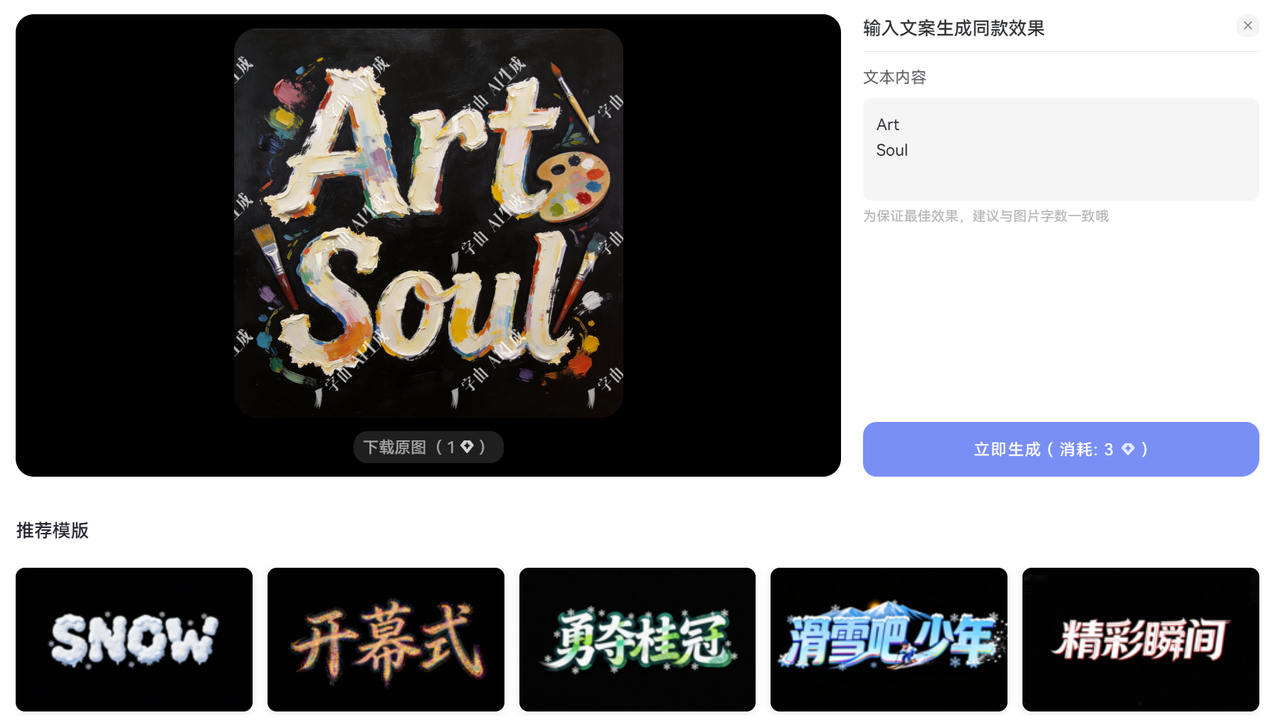
轻松自制二次元字体,分享4款好用的二次元字体生成工具
字体在二次元这个颜值至上的创作世界里,是极具辨识度的视觉核心。一款贴合风格的二次元字体,不仅能传递文字信息,更能渲染画面氛围、契合创作调性。很多朋友可能觉得 “二次元字体制作” 听起来门槛超高,但别担心,我今天就是来给大家 “降维打击” 的,推荐一些无论是萌新爱好者还是资深设计达人,都能轻松上手的二次元字体制作工具。
字由网:零基础也能秒出二次元字体的 AI 神器
说到二次元字体制作,字由网(https://www.hellofont.cn/font-tools)的 AI 字体功能必须放在首位,哪怕是刚接触字体设计的新手,也能在几分钟内做出有质感的作品。
打开字由网顶部的菜单栏的 AI 字体工具页面,首先会被它丰富的模板库惊艳到。这里的模板不是简单的字体样式堆砌,而是精准匹配二次元常见风格 。
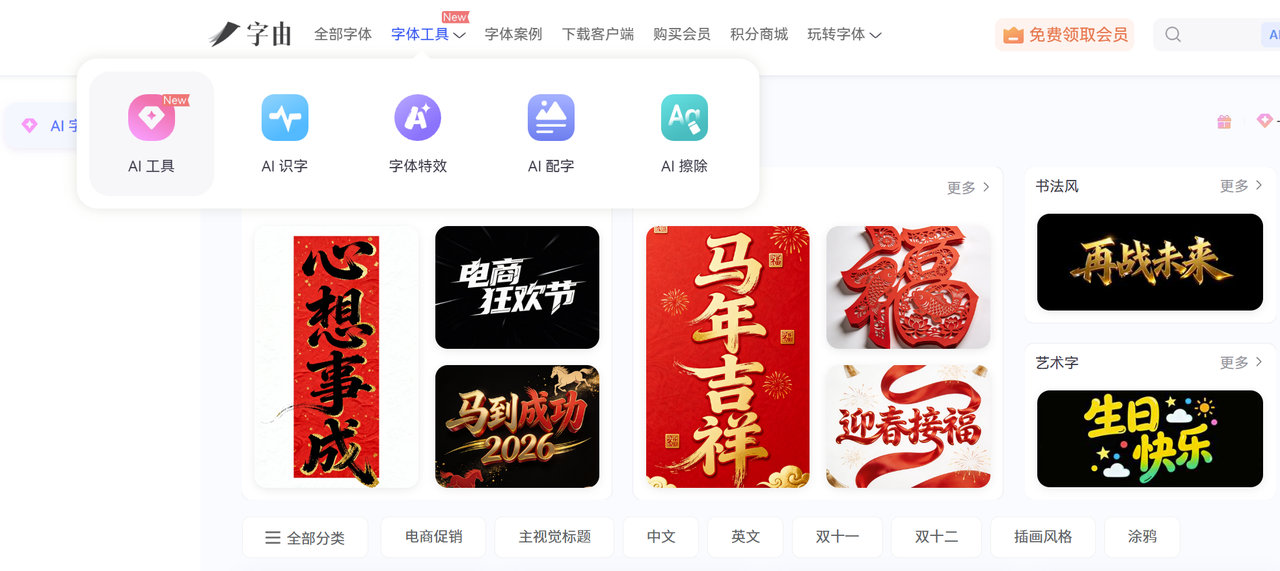
操作过程更是简单到 “傻瓜式”:先在模板库中选中心仪的风格,点击进入编辑页面后,直接输入想要生成的文字,比如 “再战未来”“生日快乐”,系统会在 3 秒内生成对应的特效字体图片。
生成的字体不仅风格统一,还支持透明背景下载,下载后能直接导入 PS、剪映等工具进行二次创作,无论是做漫画封面标题,还是视频动态字幕,都能无缝衔接。
字由网的 AI 字体模板会定期更新,紧跟二次元潮流趋势,比如近期热门的 “赛博朋克光效字”“复古像素字” 都能及时找到。对于想快速出效果、又没有设计基础的用户来说,字由网绝对是性价比最高的选择。
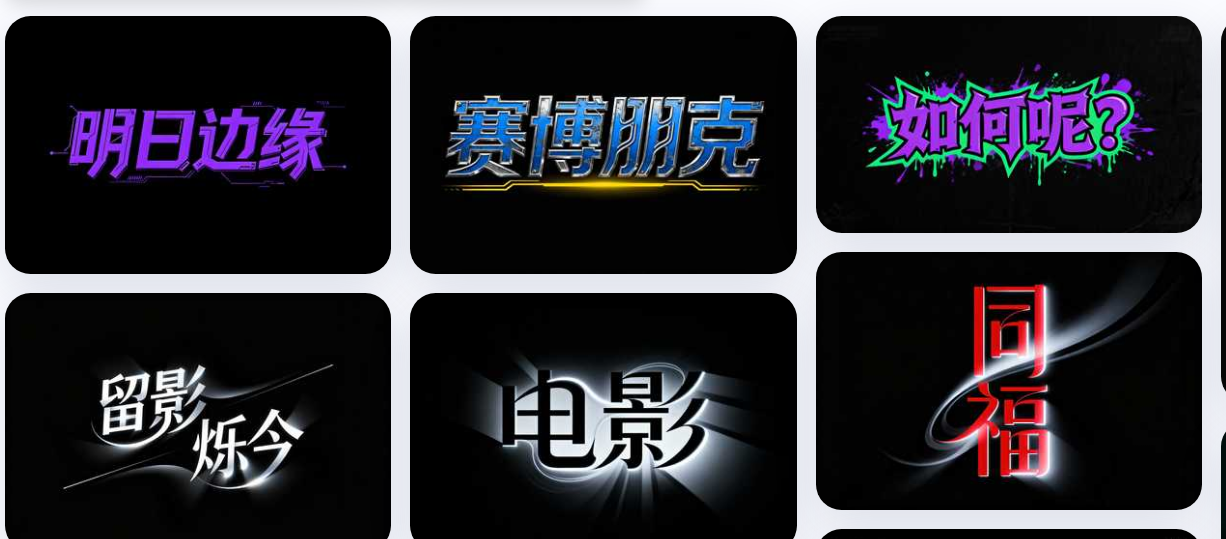
Clip Studio Paint:动漫迷专属的手绘字体优化工具
如果你想让二次元字体更有 “手绘温度”,不满足于 AI 生成的标准化效果,那 Clip Studio Paint(简称 CSP)绝对是不二之选。这款软件是动漫圈的 “宝藏工具”,不仅能画漫画,在字体设计上也有独特优势。最适合二次元创作的是它的 “特效字辅助工具”,比如制作漫画中的拟声词 “轰!”“咻~~”,可以用 “自由变换” 工具把字体拉长成速度感十足的形状,再用 “喷溅笔刷” 在笔画边缘添加墨水飞溅效果,瞬间让文字 “活” 起来。
FontSpace:免费二次元字体库 “富矿”
如果只是偶尔需要使用二次元字体,不想花时间自己设计,那 FontSpace 这个免费字体网站就能帮上大忙。它收录了上万款风格各异的字体,其中二次元主题字体数量超多,而且很多支持免费商用。在网站搜索栏输入 “Anime”“Manga” 等关键词,就能找到大量适配二次元场景的字体。
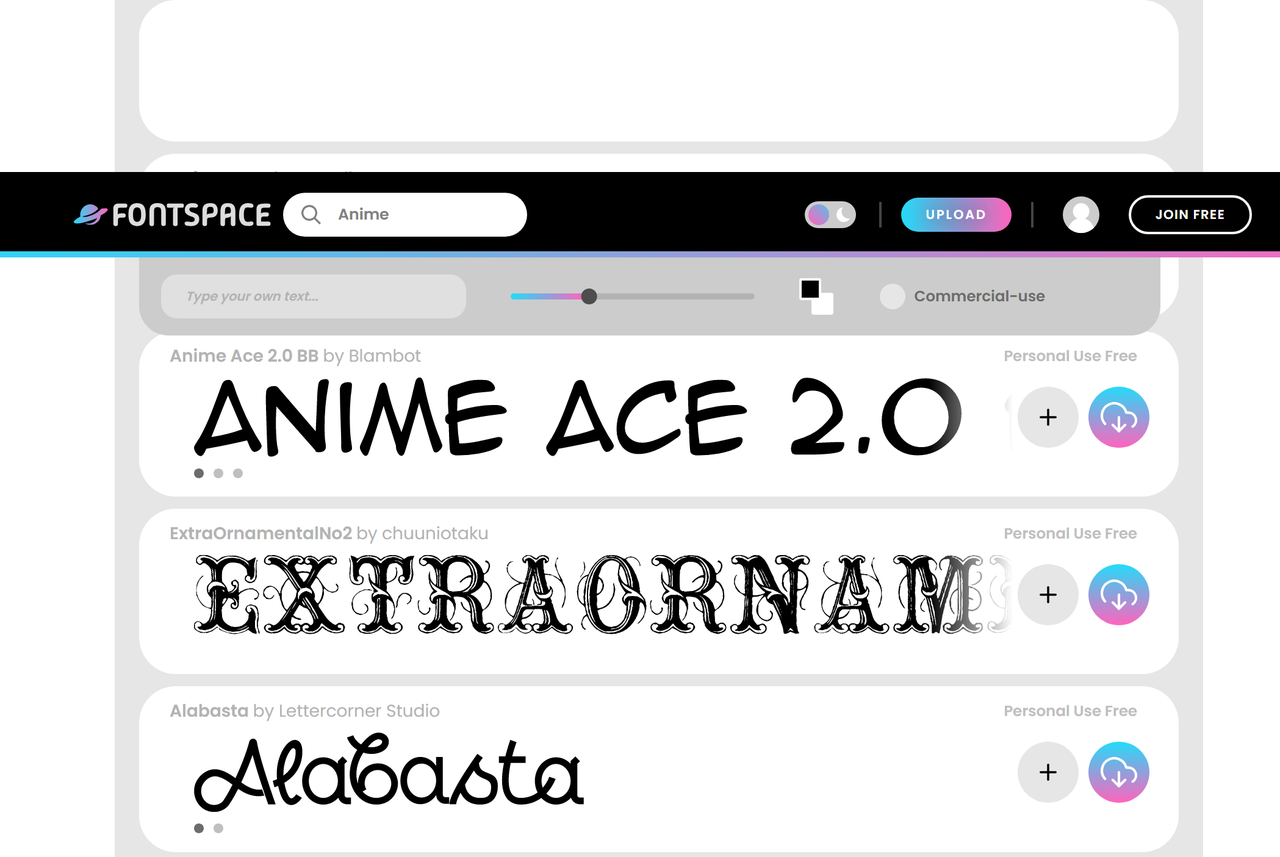
Photoshop:细节控的二次元字体 “精修师”
虽然 Photoshop 不是专门的字体设计软件,但它的图层样式功能,却是二次元字体 “精修” 的好帮手。尤其是想给字体添加立体效果、特殊纹理时,PS 的优势特别明显。PS 还能手动调整字体细节,比如用 “直接选择工具” 拖动锚点,让笔画变得不那么规整,模拟手绘感。对于需要精细调整字体效果的用户来说,PS 能让原本普通的字体 “华丽变身”,特别适合制作二次元文字。
无论是个人创作漫画、游戏 UI,还是商业设计电商海报、视频字幕,总有一款工具能契合你的需求。不用再被 “不会设计” 束缚创意,选对工具,就能让你的二次元字体既个性十足,又贴合场景,让每一段文字都成为视觉焦点。